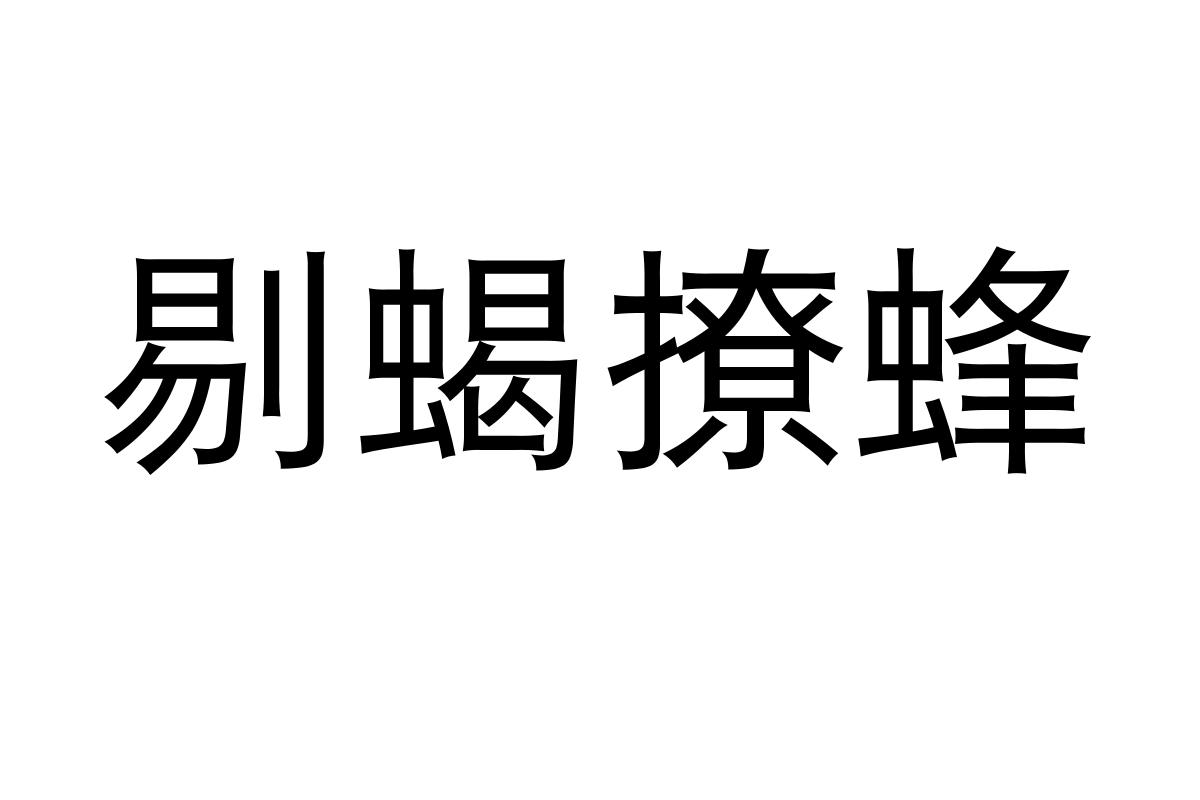
汉仪君黑-55字体是一款具有现代感的中文字体,适用于各种商业和正式场合。这款字体的特点是笔画清晰、结构紧凑,给人一种简洁明了的感觉。它的线条流畅,易于阅读,适合制作标题、正文和广告等文字内容。此外,汉仪君黑-55字体还具有一定的艺术感,可以用于设计一些具有个性和创意的作品。总的来说,这款字体是一款非常实用的商业字体,值得您尝试使用。